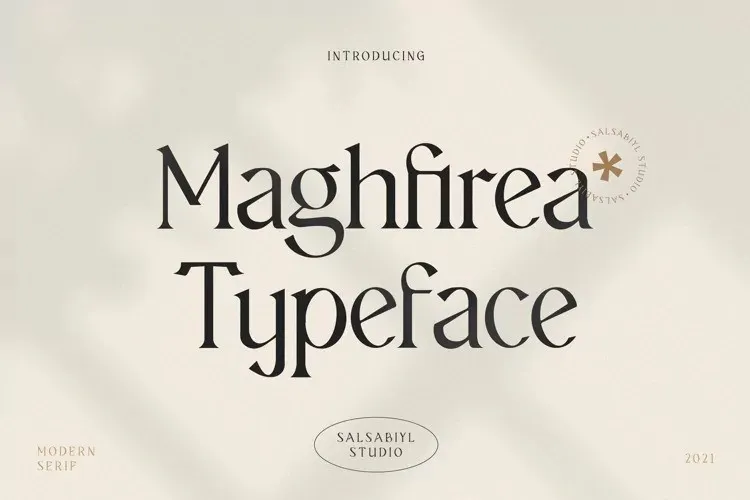
A Maghfirea Font é uma serifada única com alta contraste, produzida pela salsabiylstudios. Esta fonte serifada oferece muitos caracteres e suporta idiomas múltiplos. Ideal para quem busca estilos de design moderno, minimalista, elegante e simplesmente bonito, a Maghfirea é uma escolha perfeita. Se você está procurando por um estilo visual que seja ao mesmo tempo clássico e sofisticado, essa fonte será certamente algo que lhe chamará atenção. Com sua alta contraste e design suave, a Maghfirea traz beleza sem igual para os projetos digitais, tornando-a uma escolha ótima para designers atentos ao detalhes e à estética do design moderno.